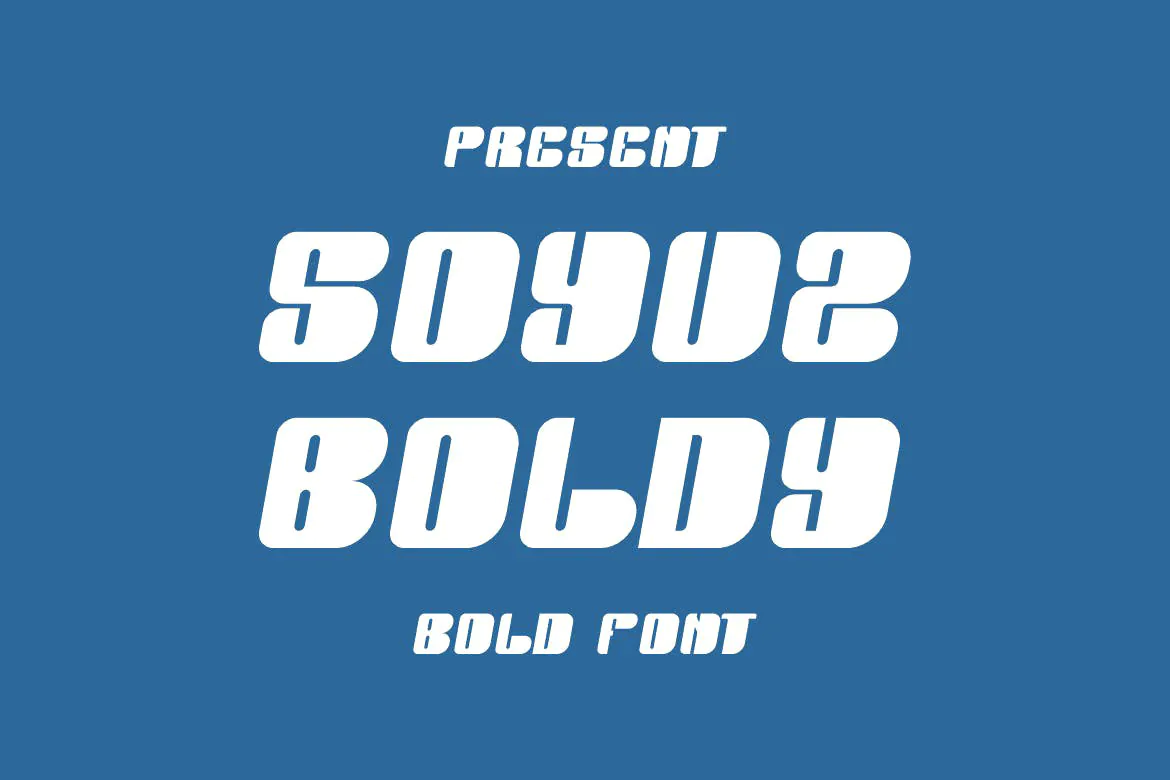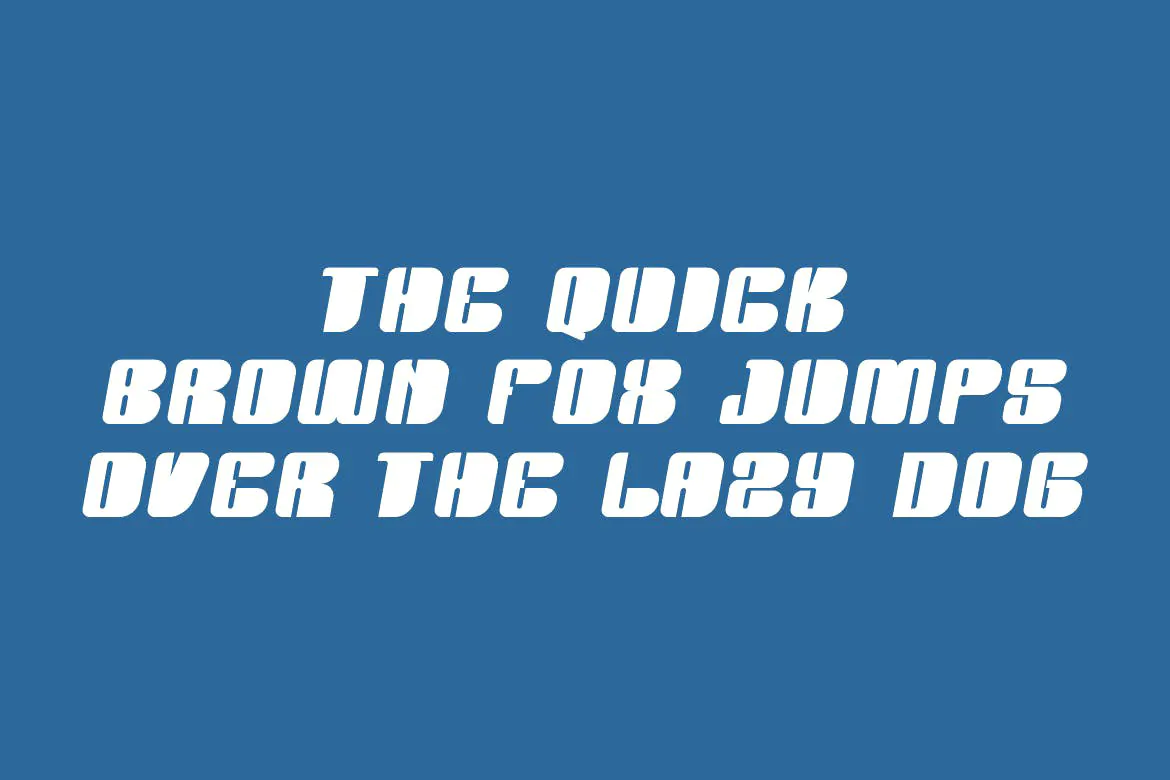
فونت لوگو تایپ Soyuz Boldy
فونت لوگو تایپ Soyuz Boldy یک قلم انگلیسی فوق العاده زیبا است که به صورت ضخیم یا بولد طراحی شده است و مناسب برای استفاده در طراحی لوگو، پوستر، بسته بندی محصولات، رسانههای اجتماعی و … میباشد.